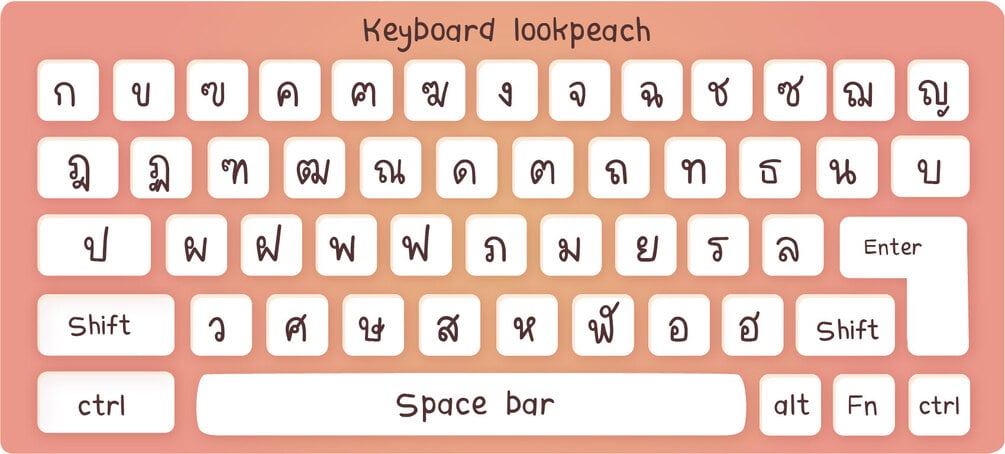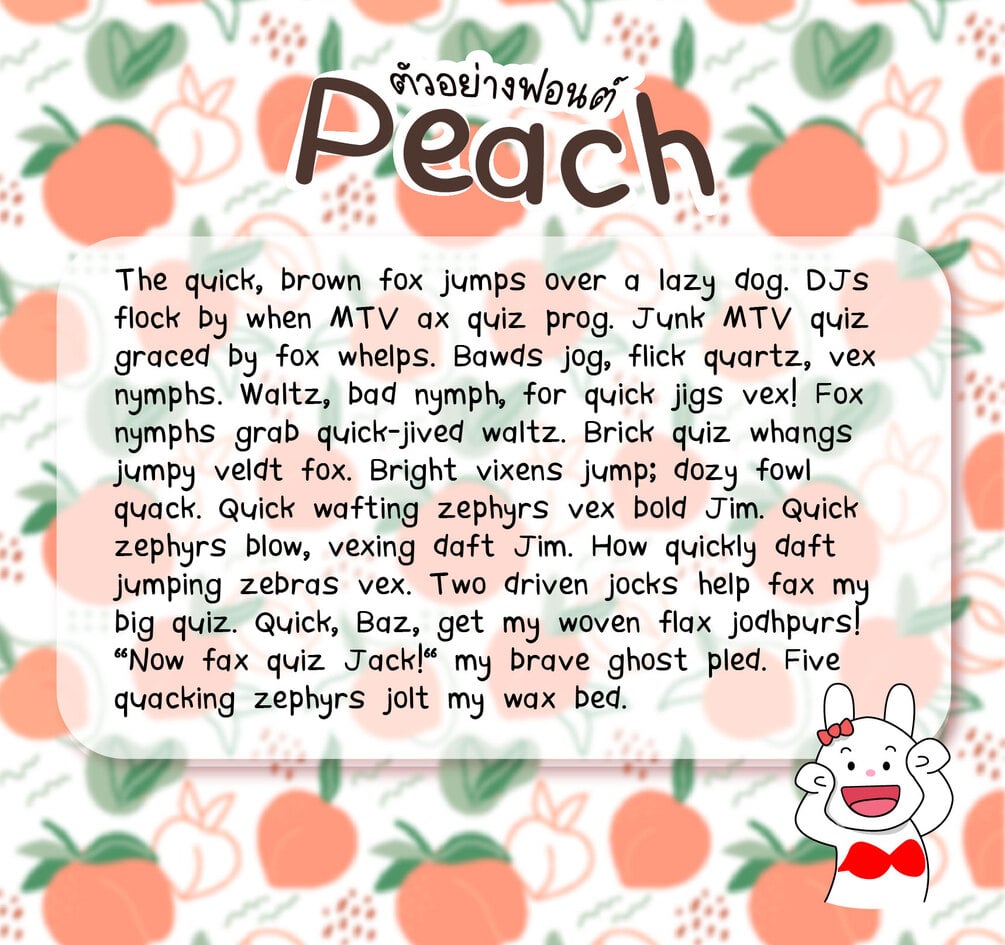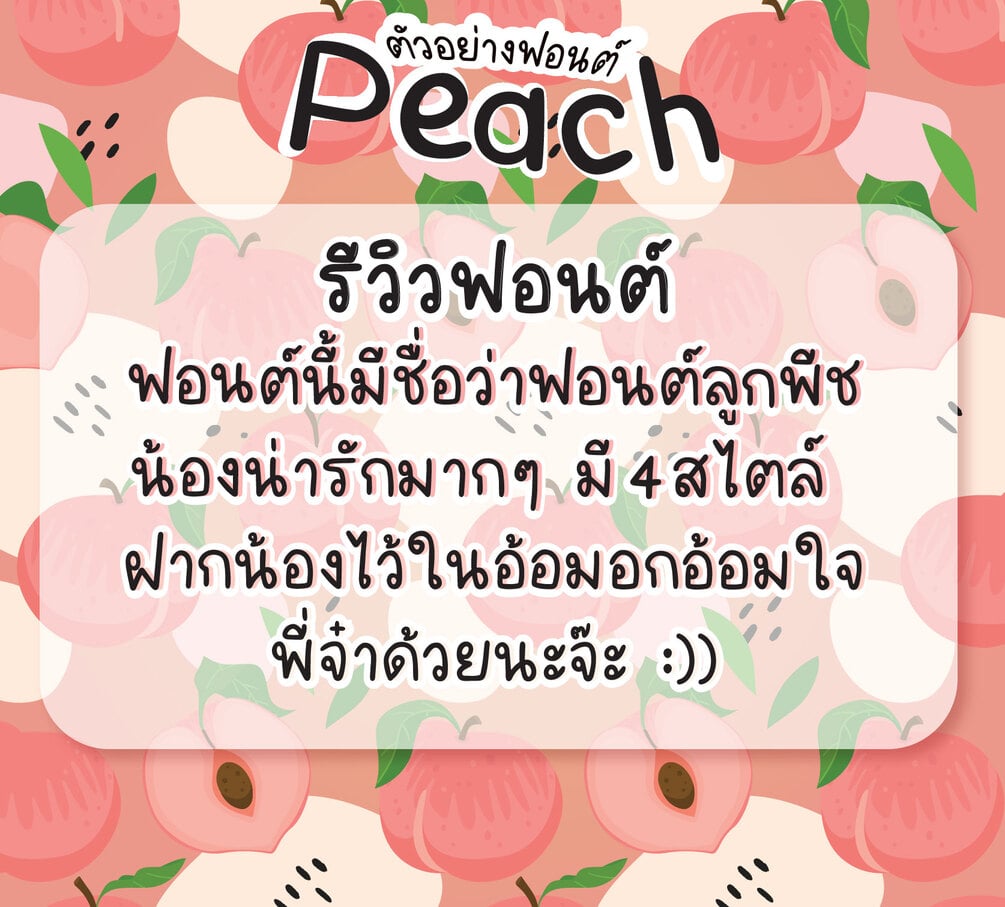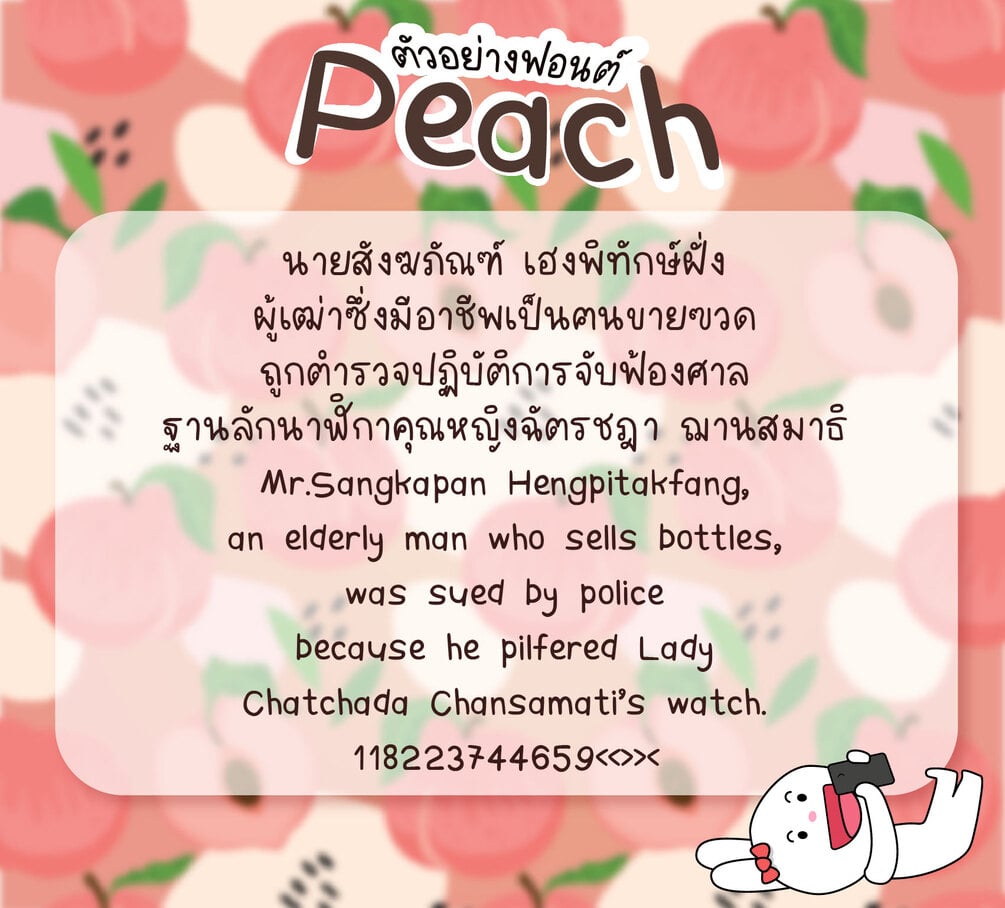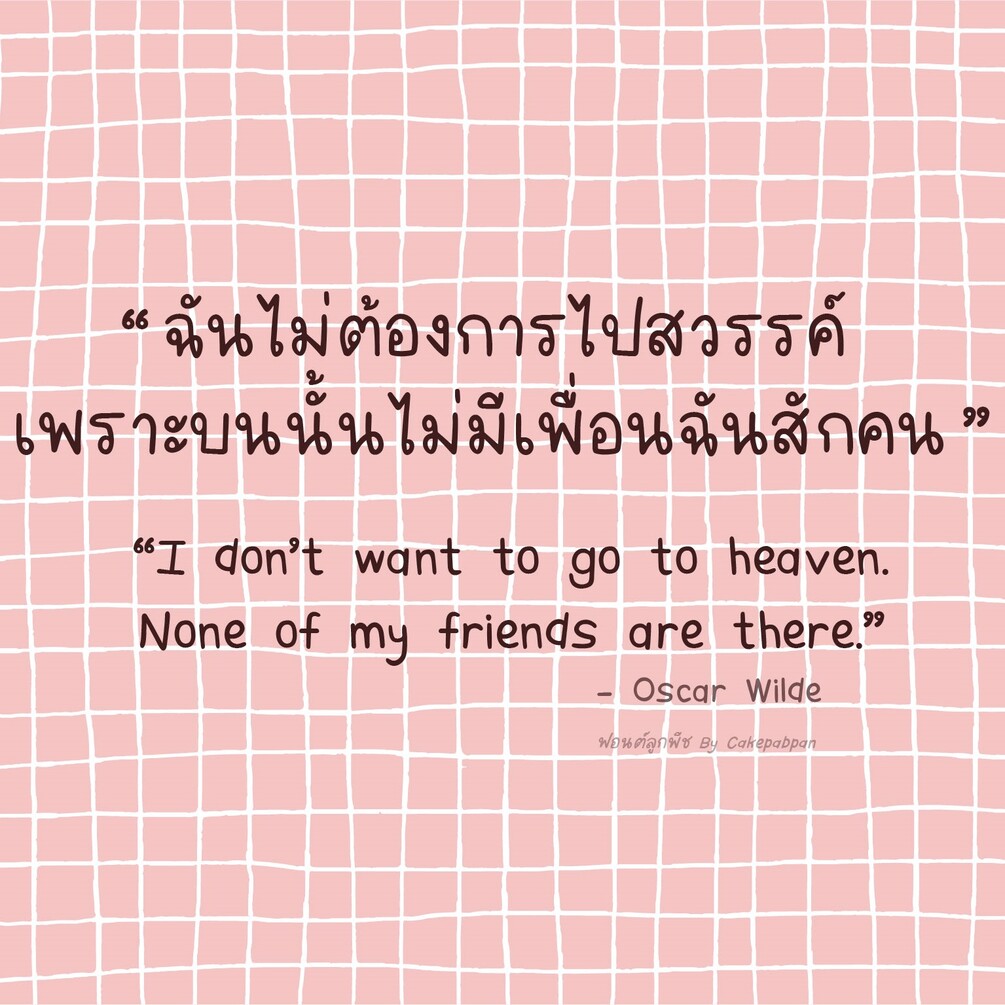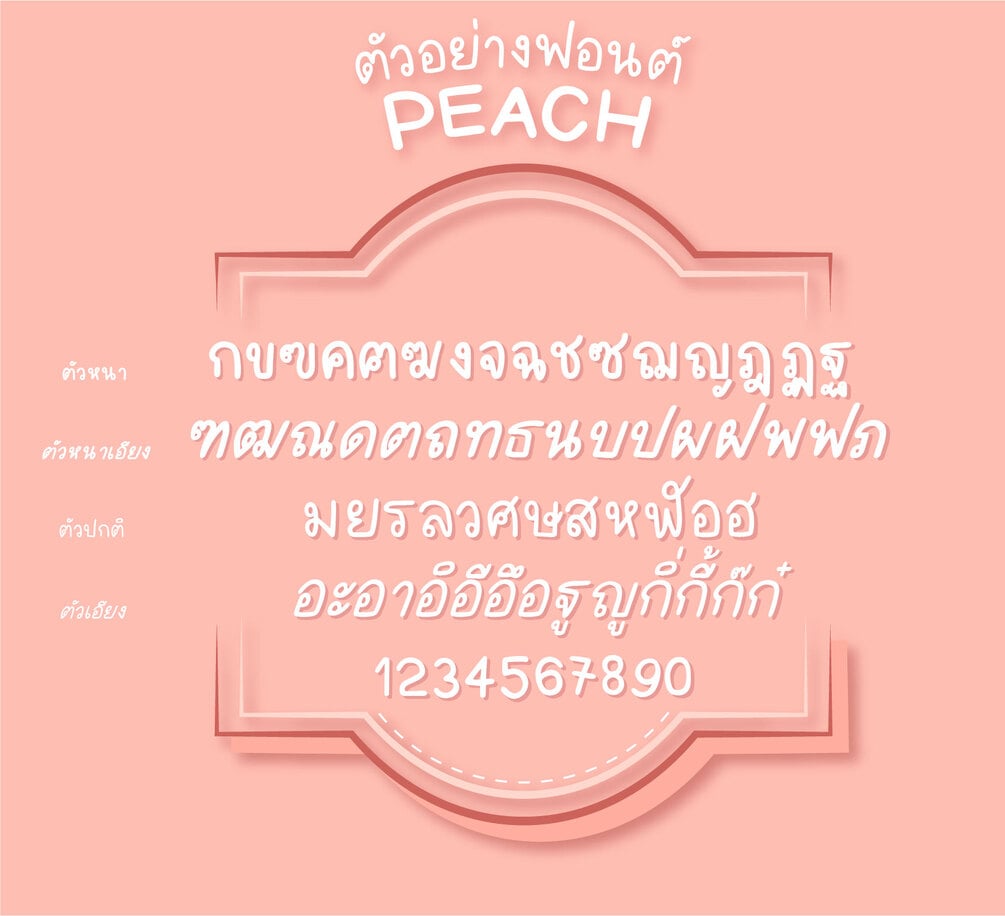
Lookpeach Font (ฟอนต์ลูกพีช)
ฟอนต์ลูกพีช 🍑🍑 สุดคิ้ววว มีด้วยกัน 4 น้ำหนัก (ตัวปกติ ตัวหนา ตัวเอียง และตัวหนาเอียง)
สามารถใช้ได้ทั้งภาษาไทย และภาษาอังกฤษ มีเลขอารบิก เลขไทย และสัญลักษณ์ทางคณิตศาสตร์บวกลบคูณหารพร้อม!